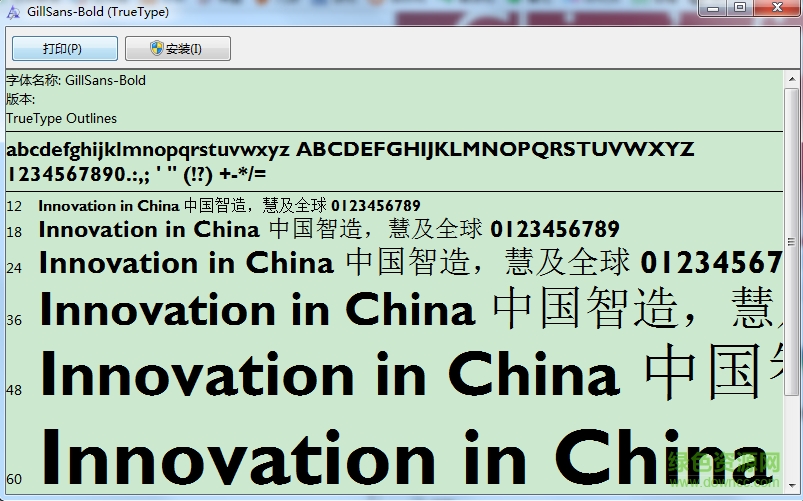
gillsans semibold是一款無襯線英文字體,這款字體轉(zhuǎn)角柔和,十分具有親和力,整體效果非常出色,喜歡的朋友歡迎來綠色資源網(wǎng)下載使用。
無襯線體(Sans-serif)專指西文中沒有襯線的字體,與漢字字體中的黑體相對應(yīng)。與襯線字體相反,該類字體通常是機(jī)械的和統(tǒng)一線條的,它們往往擁有相同的曲率,筆直的線條,銳利的轉(zhuǎn)角。